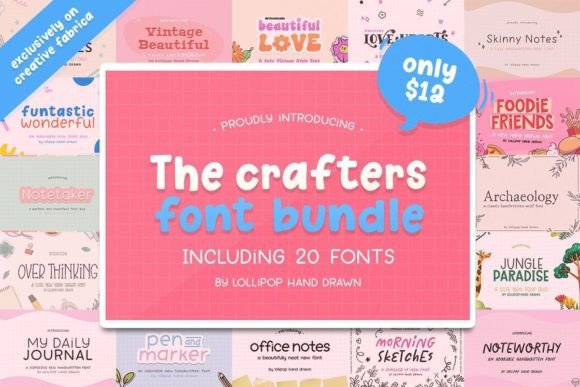
The Crafters Font Bundle - Vol 01
Jika anda sedang mencari aset berkualiti tinggi seperti The Crafters Font Bundle - Vol 01, pakej premium ini merupakan pilihan yang hebat untuk projek kreatif anda.
Sama ada anda mencipta produk POD (Print on Demand), jemputan perkahwinan atau grafik media sosial, The Crafters Font Bundle - Vol 01 amat bersesuaian.